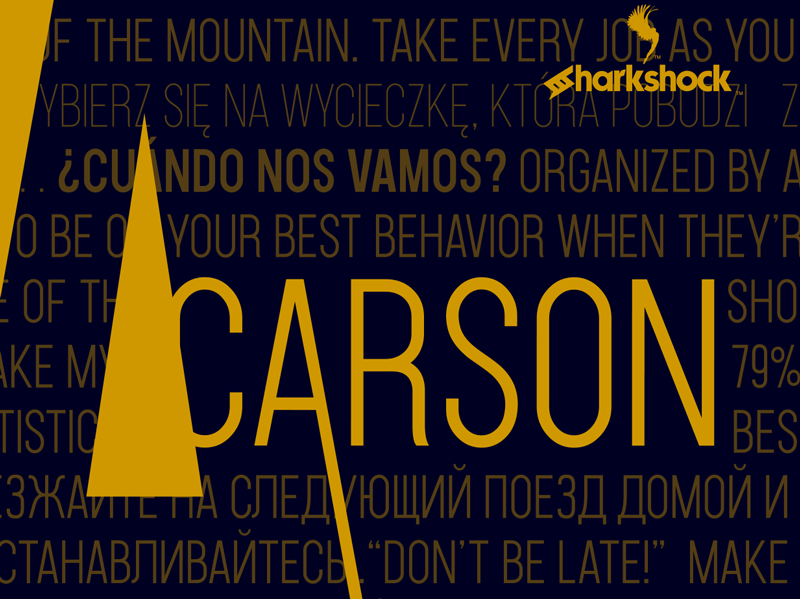
A Carson Font Family é uma famosa família de linhas gerais criada pela Sharkshock para se encaixar no formato sem serif dos títulos e subtítulos. Embora seja um sistema em letras maiúsculas, a Carson oferece três pesos diferentes que podem ser usados a qualquer momento. Suas linhas são levemente contrastantes por causa de seu modo bold, destacando ligeiramente alguns destes contornos com uma linha mais fina para criar um leve contraste. A Carson é idealmente projetada para espaços estreitos e tem uma natureza vertical, facilitando sua aplicação em diversos ambientes. Seja ela usada em livros, subtítulos de sites ou logotipos de empresas, a Carson garante que seu design seja destaque sem distorções desnecessárias. A sua versatilidade torna-a uma excelente opção para designers gráficos de todo o Brasil e mundo.